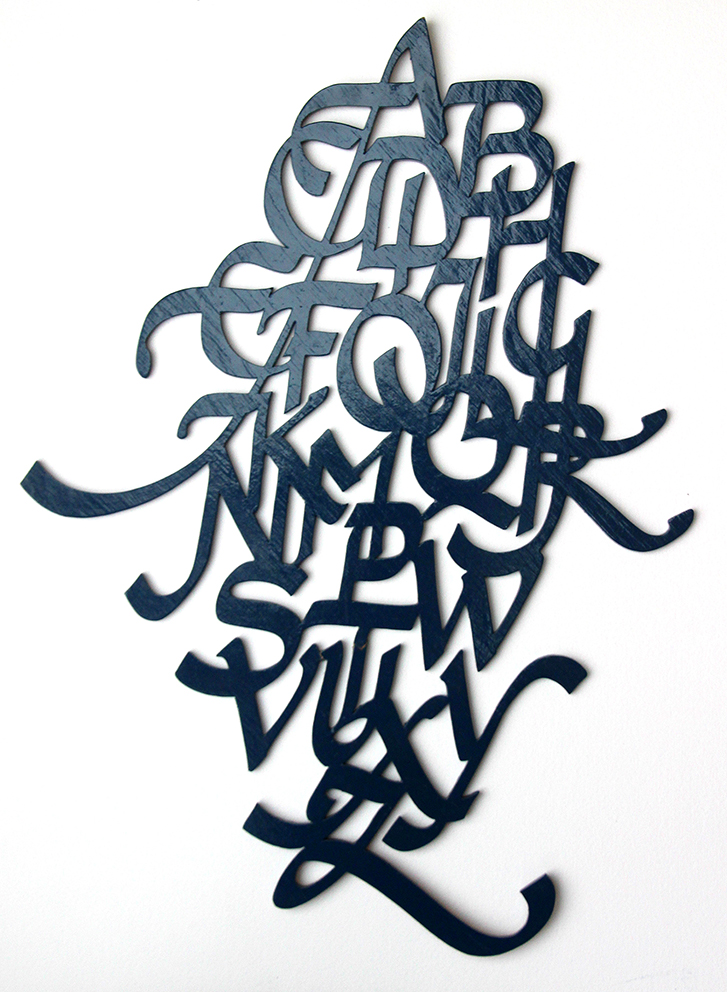
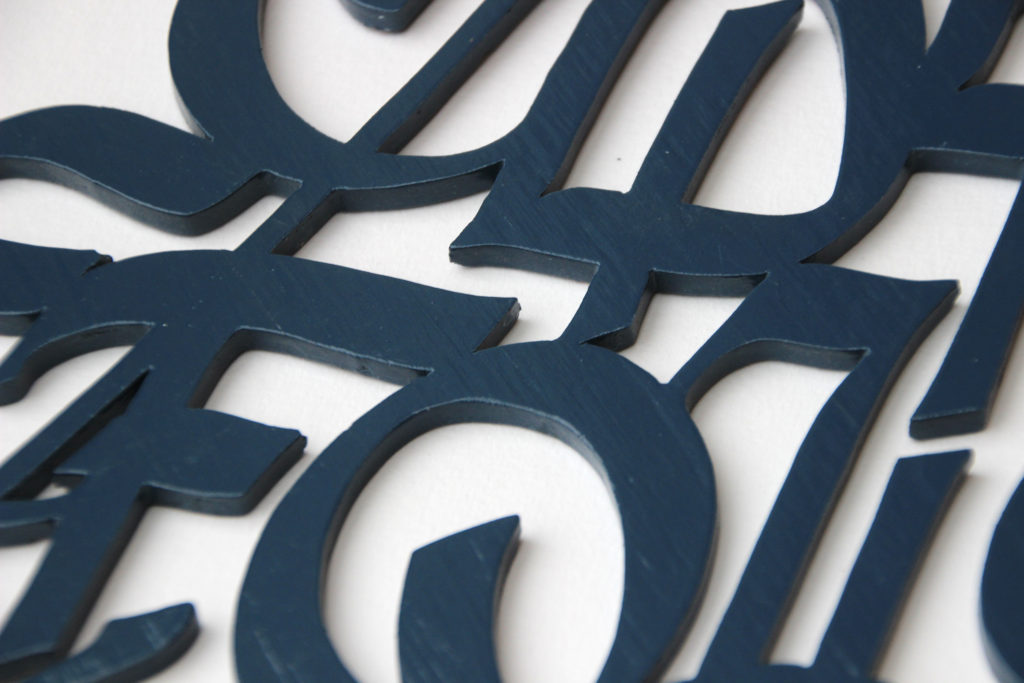
Dit is een oudje, uit 1985. Niet met pen op papier, maar gefiguurzaagd uit één stuk triplex. Waarom ook niet? Je kunt kalligraferen met allerlei gereedschappen en materialen. Je ziet hier het alfabet. Eerst de losse letters op papier getekend en al schuivend tot een compositie gemaakt, zó dat het een weefwerk werd zonder te grote gaten of dikke klonten. Dan op het triplex overtrekken en zagen maar! Daarna geverfd. Van hout dus, maar óók kalligrafie – ondanks het feit dat dat woord letterlijk ‘mooi schrijven‘ betekent. Formaat: 46 x 33 cm.